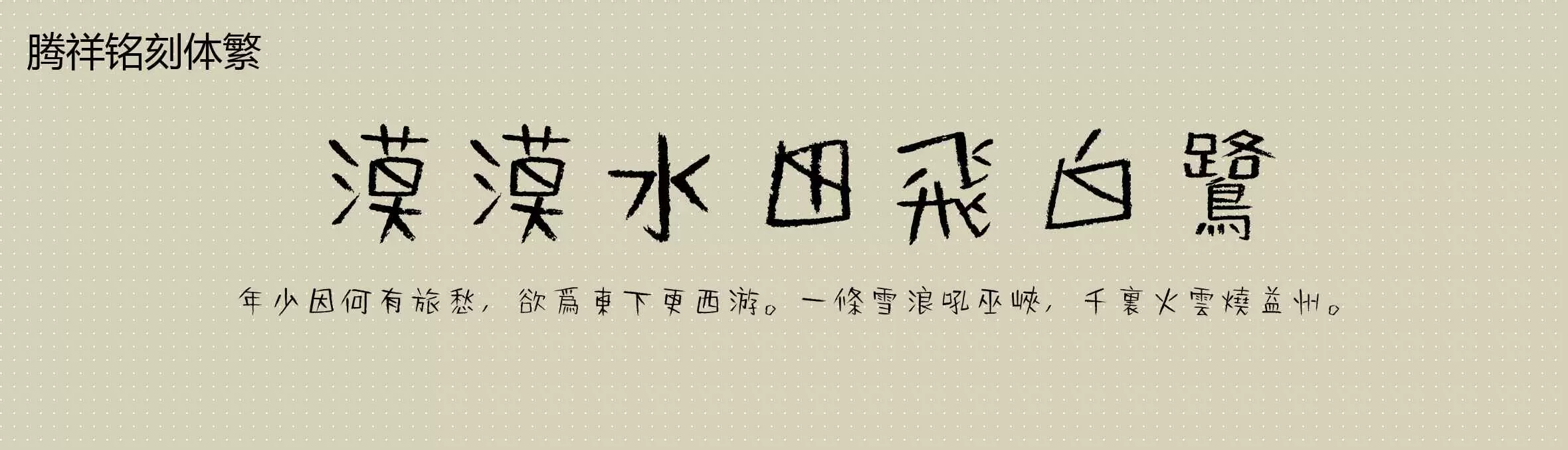
腾祥铭刻体繁体由设计师孔淼先生书写完成字体初稿,再由腾祥公司二次设计制作成的手写体字库。风格鲜明、特点突出。笔画古朴雅拙、精雕细刻。笔画犹如用刀在石壁上一笔笔刻画出的图案。笔笔劲力、力透纸背、飞白显露,彰显刀刻之功。字形大小有别;笔画粗细有致,看似不经意却实则有意而为之,在经意与不经意间寻求平衡,浸透设计师书写功力。本作品可适用于包装设计、广告设计、网页设计等。